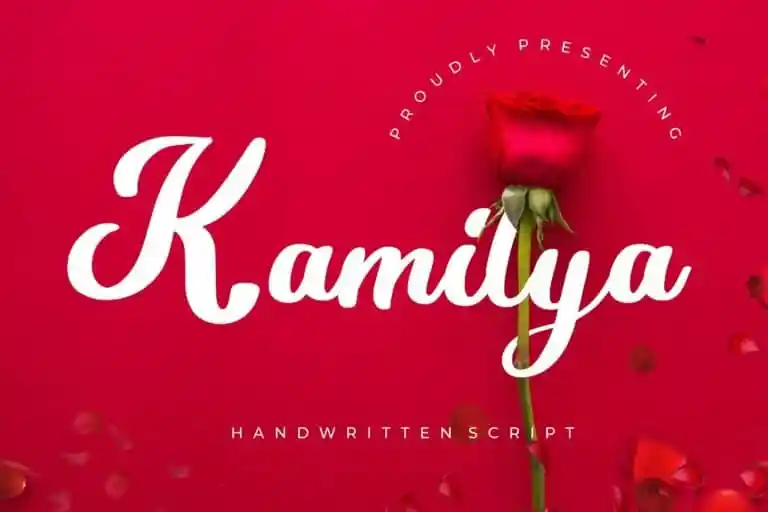
Kamilya Script Font – Download Grátis
A Kamilya Script Font é uma criação única que brota diretamente do universo do tipo à mão. Ela surge a partir das ideias enxutas e criativas dos desenhos manuscritos, um trabalho meticuloso que reflete o domínio de artistas talentosos da Creatype Studio. Esta fonte é uma invenção moderna e jovial, incorporando elementos de escrita manual e tipográfica com um toque refinado e natural. Perfumada com a essência de um estilo script elegante e sofisticado, ela transmite aos projetos a sensação perfeita de uma escrita real. Com seu design revigorante e sua aparência envolvente, Kamilya Script é ideal para os designers que desejam trazer um toque único à sua obra, seja em cartazes grandiosos ou em letras finas para blogs e sites pessoais. Ideal para aqueles buscando uma font que expressa elegância e naturalidade em conjunto, ela se adapta perfeitamente a diversas necessidades gráficas. Seja você designer de lojas online, criador de conteúdo no Instagram ou até mesmo um blogueiro aficionado, Kamilya Script está sempre pronto para ajudar a trazer vida à sua ideia, tornando cada projeto ainda mais especial.